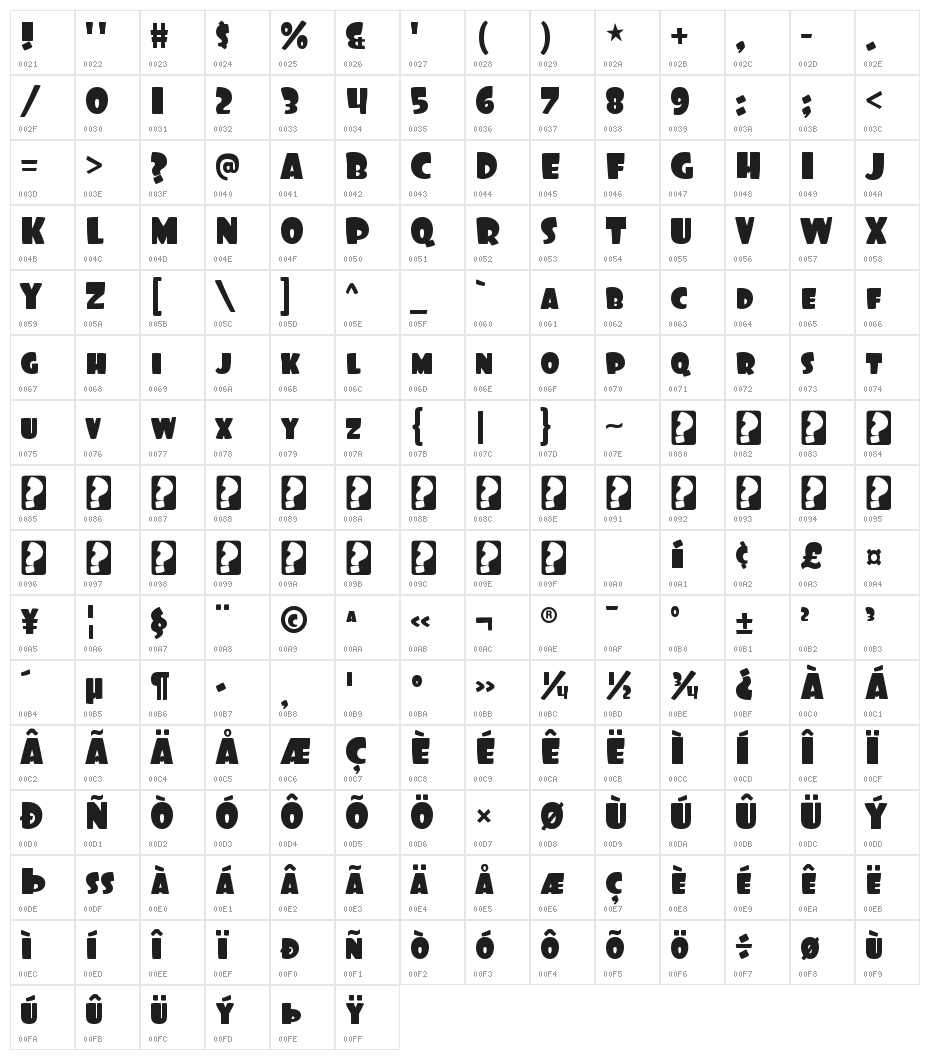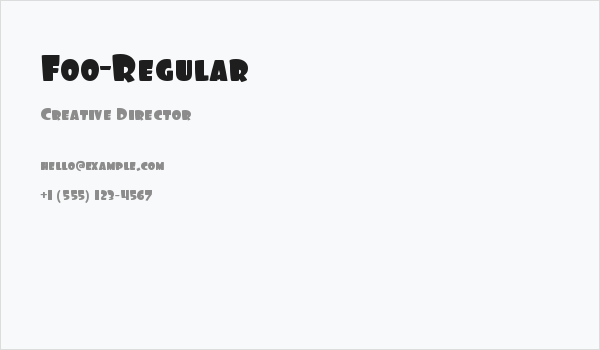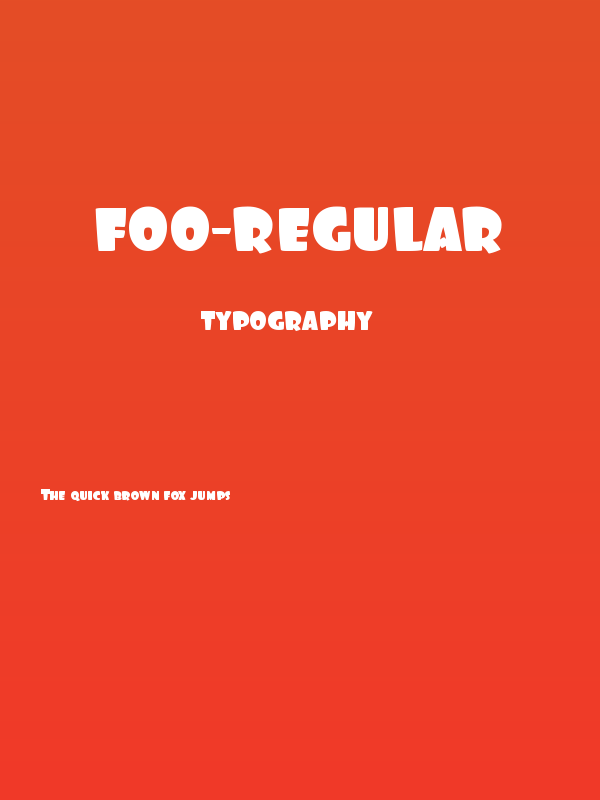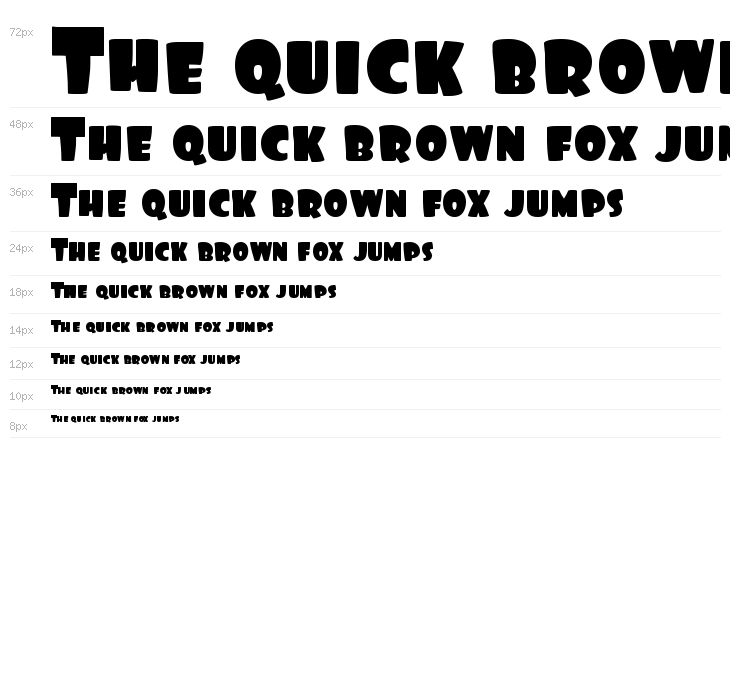
Foo-Regular Font
| Общий стиль | Playful, Whimsical |
| Рекомендуемые проекты | Ideal for children's books, playful branding, party invitations, and casual posters. |